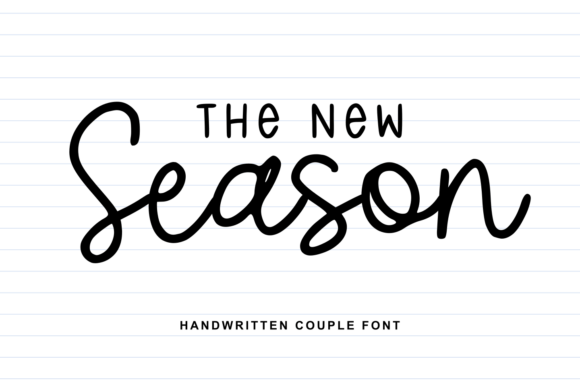
New Season Duo
Om du letar efter högkvalitativa tillgångar som New Season Duo, är detta premiumpaket ett fantastiskt val för dina kreativa projekt.
Oavsett om du skapar POD-produkter (Print on Demand), bröllopsinbjudningar eller grafik för sociala medier, är New Season Duo ett perfekt val.